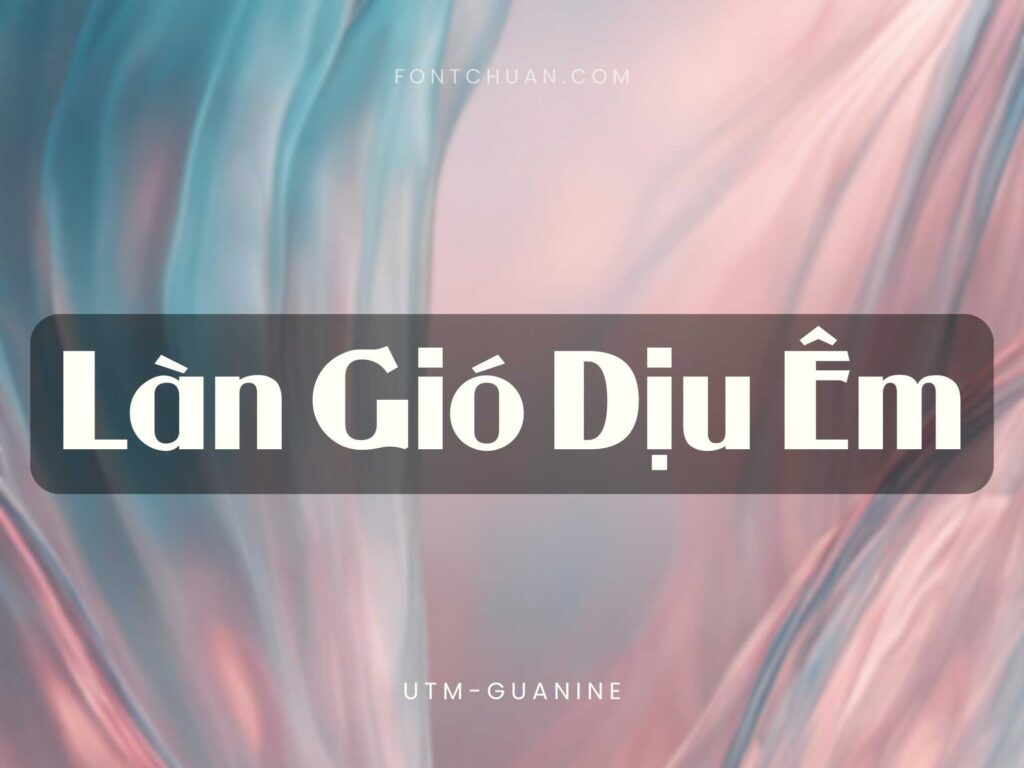
UTM Guanine là một font chữ hiện đại với phong cách mạnh mẽ, được thiết kế nhằm mang đến sự độc đáo và sáng tạo trong thiết kế đồ họa. Font này đã được Việt hóa bởi Thiên Minh, hỗ trợ tiếng Việt cùng hơn 200 ngôn ngữ khác, giúp mở rộng khả năng ứng dụng trong nhiều lĩnh vực. Thành viên của Font Chuẩn đã sưu tầm và giới thiệu font này nhằm đáp ứng nhu cầu bạn đọc, mang đến nguồn tham khảo chất lượng và ứng dụng thực tế vào các dự án thiết kế
Về đặc điểm thiết kế, UTM Guanine có cấu trúc chữ cân đối, độ tương phản cao và đường nét sắc sảo, phù hợp với những thiết kế đòi hỏi sự nổi bật và cá tính. Font này lý tưởng cho các dự án quảng cáo, thiết kế bao bì, biển hiệu, và nội dung kỹ thuật số. Các ngành nghề như công nghệ, quảng cáo, giáo dục và thiết kế thương hiệu có thể sử dụng font này để tạo điểm nhấn và tăng tính chuyên nghiệp trong các sản phẩm thiết kế